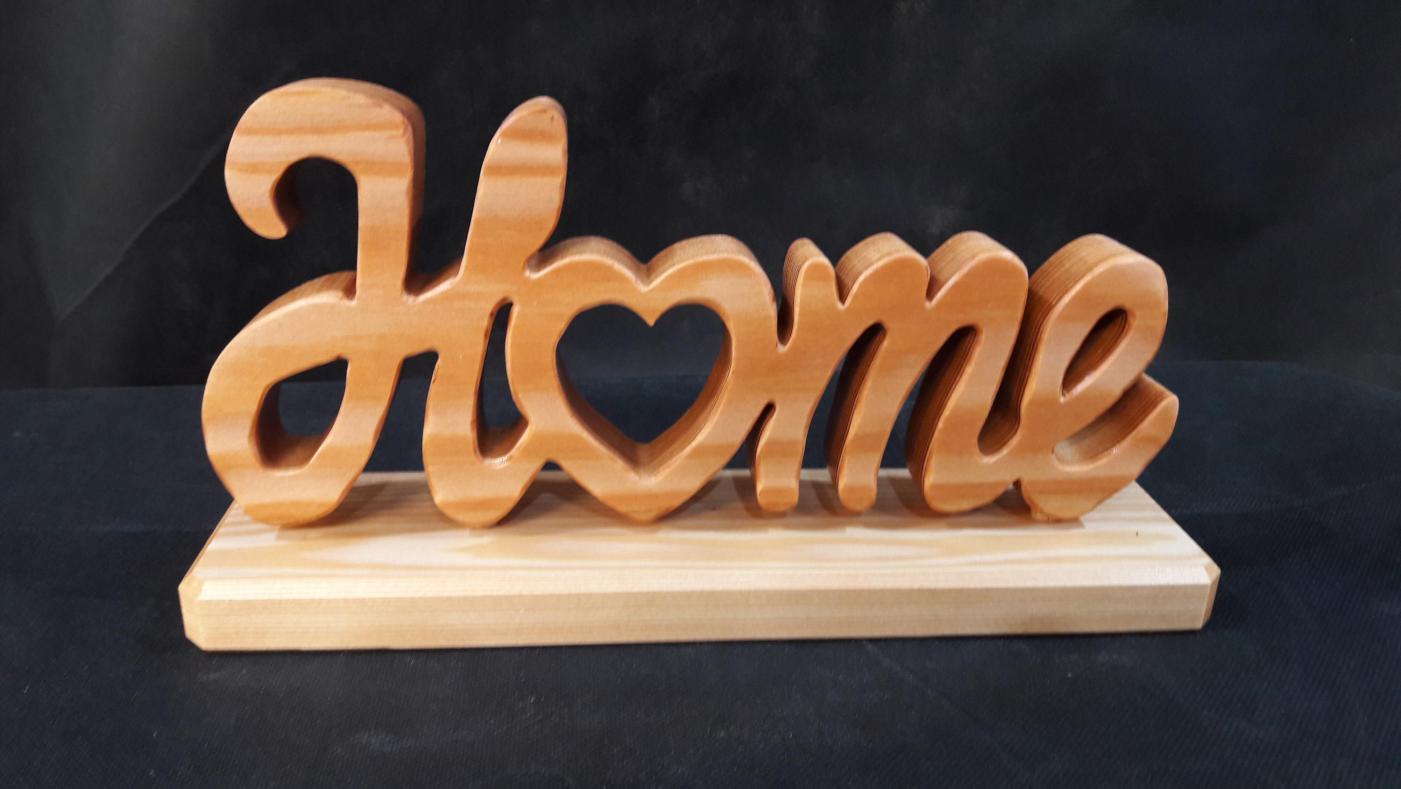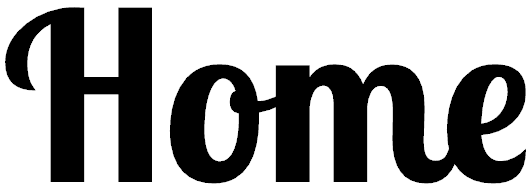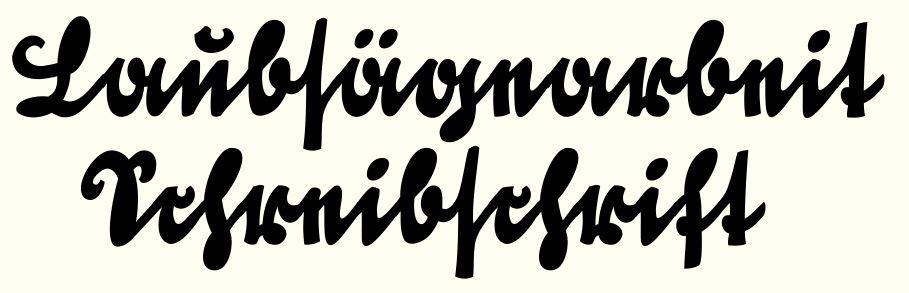
Geschwungene Handschrift für Laubsägearbeiten
hallo, suche eine etwas dickere handschrift die keinen abstand zwischen den buchstaben hat, schwierig denn wenn ich aus einer holzplatte ein a oder o usw. ausschneiden möchte, fällt dieses ja raus. die ganzen stencil buchstaben oder wie die heißen gefallen mir nicht, es sollte eine schöne geschwungene sein, wo z.b bei einem buchstaben o dies nicht ganz den ovalen kreis schliesst. suche schon so lange :(
desweiteren bräuchte ich noch so eine ähnliche wie auf dem bild zu sehen ist, für stehende schriftzüge aus holz.
So etwas? http://www.dafont.com/de/love3.font?text=Home
Oder eher so etwas? https://www.fontsquirrel.com/fonts/lobster-two?q[term]=Lobster&q[search_check]=Y
Die Lobster Two ist meiner Meinung nach ganz gut für solche Laubsägearbeiten geeignet, da sie sehr statisch ist aber dennoch geschwungen ist:
Oder doch so etwas? https://www.behance.net/gallery/41089697/Hensa-Free-Brush-Script-Typeface
Du kannst aber auch selber nach Script-Fonts suchen, die dir gefallen: https://www.myfonts.com/search/tag%3Ascript/fonts/?sort=sales
Hier gibt es kostenlose Script-Fonts: https://www.fontsquirrel.com/fonts/list/classification/script
Wäre ich eine Stencil-Schrift, dann würde ich mir jetzt beruhigt den Schweiß ausgestandener Angst von der Stirn wischen.
Angenommen, du hättest eine Stencil-Schrift, bei der das o an zwei Stellen durchbrochen ist, dann müsstest du beide Einzelteile auf der Grundplatte befestigen. D. h. für deinen Zweck wäre eine Stencil-Schrift schon aus technischen Gründen eher ungeeignet. Die abgebildete Laubsägearbeit ist ein Positiv. Eine Stencil-Schrift bräuchtest du für das Negativ.
Und was spräche eigentlich dagegen, jeden Buchstaben einzeln auf die Grundplatte zu montieren?
Das mussten wir mal im Technik-Unterricht machen. Aus Holz Buchstaben aussägen und dann auf eine Grundplatte kleben.
...erst mal Danke für die Antworten! Nein, kann die Buchstaben nicht Aufkleben, das werden Herzen aus Massivholz mit ausgesägten Namen, stelle Morgen ein Foto ein.
Ich glaube, hier war das Beispielbild etwas missverständlich gewählt. Wie ich den Text verstanden habe, soll die Schrift als Durchbruch im der sonst geschlossenen Holzplatte erscheinen, und dabei eben die Punzen noch mit der Platte verbunden bleiben. Hab ich das so richtig verstanden?
Quasi als Negativ-Schrift? (Um es einfach zu sagen)
Also im Prinzip so etwas ähnliches wie dies hier:
ja super, nur müsste es besser zu lesen sein, aber im prinzip genau so etwas...
Jetzt habe ich es auch verstanden :gimmifive:. Ich hoffe morgen kommt das Foto, auf dem man sieht, wie es später aussehen soll.
Dann schreib mal noch, welches Programm du zu nutzen gedenkst, um die Schrift aufs Holz zu bringen. Es gibt nämlich viele Schriften, bei denen die Buchstaben nur richtig verbunden sind, wenn die Software eine Technologie namens Opentype beherrscht.
Na gut, dann mal ein kurzer Überblick
All dies wird leider noch immer von wenigen Programmen unterstützt, LibreOffice in der neuesten Version 5.3, Firefox oder die Adobe CC Programme gehören dazu, einige weitere unterstützen noch ein paar dieser Anweisungen, aber die Mehrzahl der für normale Menschen verfügbaren Software ignoriert das leider, und das Schreibschrift-Beispiel sieht dann so aus: